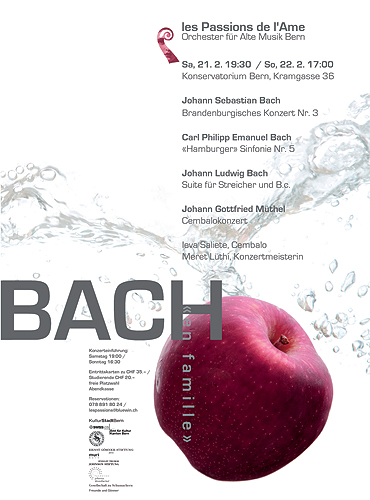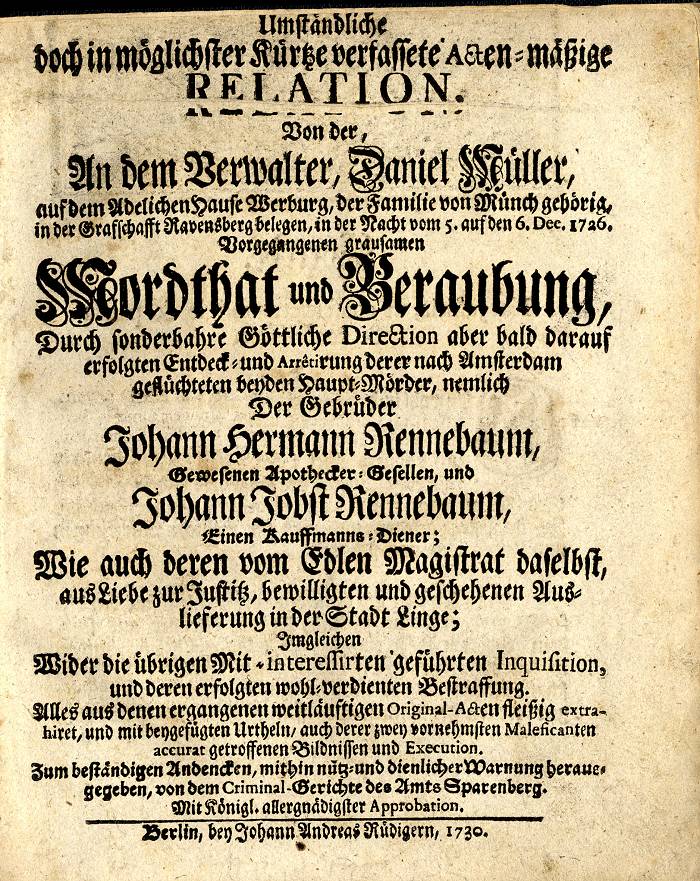
Johann Sebastian Bach
was wäre wohl die historisch korrekte Schrift wenn es darum geht Plakate für Bach-Konzerte zu gestalten? Eine gebrochene?
bach hat vom 1685 bis 1740 gelebt.
wahrscheinlich machst du mit einer garamond weniger falsch als mit einer fraktur.
wobei die heutigen formen eigentlich nichts mehr mit den damaligen gemein haben.
es sei denn, du nimmst solche fonts: http://new.myfonts.com/fonts/glc/1741-financiere
Das wäre ein Beispiel aus seiner Zeit:
Die Garamond ist allerdings weder eine barocke noch eine deutsche Schrift.
Bach war seiner Zeit natürlich weit vorraus. Aber hätte man im Jahre 1700 eine Bach-Partitur in einer französischen Renaissance-Antiqua gesetzt?
Es geht mir hier wirklich um hundertprozentige historische Akuratesse.
Ja, so ist es wohl für die Zeit korrekt gesetzt. Deutsches in Fraktur, lateinische Wörter in Antiqua. Nur hat dieser Text jetzt nichts mit Musik zu tun.
Könnte es sein, dass es für musikbezogene Schriftstücke andere Regeln gab?
Ich hoffe ich komme nicht zu klugscheißerisch rüber, ich will es nur bei dieser Sache ganz genau nehmen.
wenn du es ganz genau nehmen willst, dann brauchst du original-dokumente von bach bzw. seinen werken. bzw. ein original-plakat aus der zeit und natürlich die originalen schriften.
gab es früher überhaupt 'plakate' in der form wie wir sie heute kennen?
Dass Bach seiner Zeit voraus war heißt aber nicht dass die Setzer und Drucker dies auch waren. Vieles wurde ganz pragmatisch so umgesetzt wie es die Technik oder der Setzkasten oder das eigene Wissen zuließen. Ich bezweifle dass es überhaupt eine "hundertprozentige historische Akuratesse" gibt.
Könnte es sein dass du dich gerade etwas verkrampfst? Die Druckereien hatten keine Tausende Schriften, die ganz explizit nach Inhalt zum Einsatz kamen. Und ein Plakat in Leipzig 1745 hat sicherlich ganz anders ausgesehen als eines aus Mühlhausen 1710. Also was ist hier historisch korrekt?
Um was für Konzerte geht es denn überhaupt? Bach hat sehr viel für Gottesdienste komponiert, da wurde überhaupt nie plakatiert weil die Leute sowieso in die Kirche gegangen sind. Da erscheint es dann auch nicht sinnvoll, diese nicht vorhandenen Plakate einwandfrei nachsetzen zu wollen.
Ich will damit sagen das es nicht die richtige und historisch korrekte Typographie gibt. Das hängt vom Ort, von der Zeit, von der Druckerei, vom Auftraggeber usw. ab. Die Parameter kennen wir aber nicht …
Es geht mir gar nicht um kein konkretes Konzert. Es geht mir einfach um eine Schrift, die zu Johann Sebastian Bach passt.
Beispiel:
Mache ich ein Plakat für Miles Davis nehme ich Franklin oder News Gothic; mache ich ein Plakat für Bach nehme ich …
OK falls das jetzt wirklich so schwer zu verstehen ist:
Ich habe mich gegen die historische Korrektheit entschieden weil das anscheinend wirklich schwierig ist.
Gelegentlich sollte man im Leben mit 80%-Lösungen zufrieden sein. Also ich mein, bevor man vor den Problemen vollständig kapituliert. Sonst kauft man irgendwann einen Traktor, weil man sich nicht zwischen Focus, Golf und Astra entscheiden konnte.